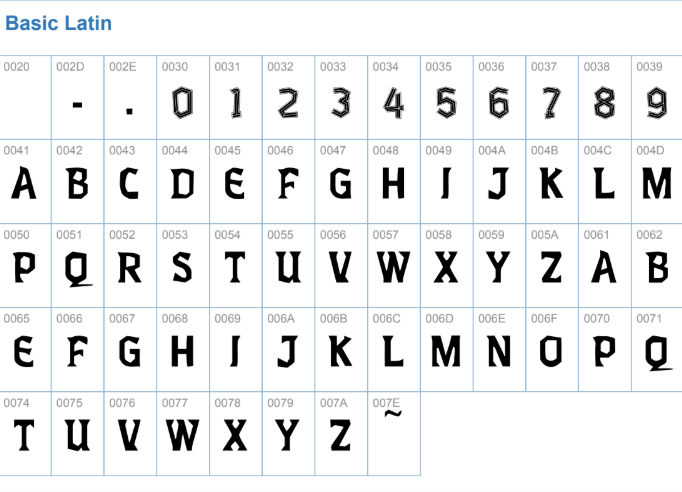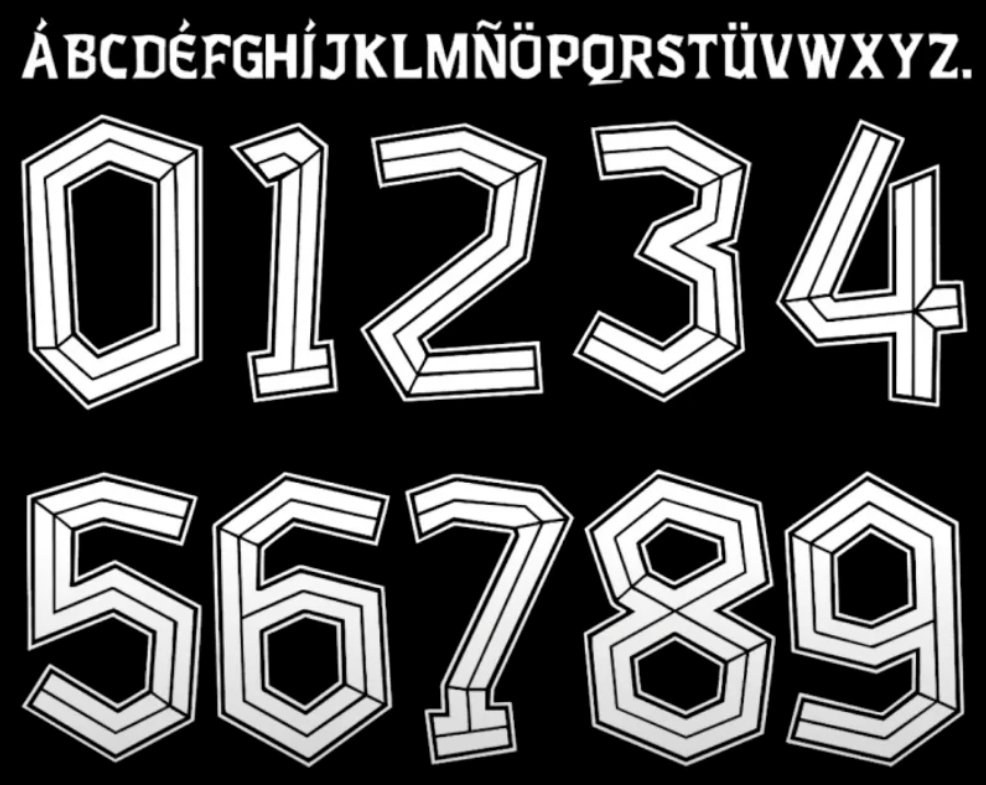
Para os apaixonados pelo Vozão e profissionais de personalização esportiva, trazemos hoje um arquivo essencial: a tipografia oficial utilizada nos uniformes do Ceará Sporting Club para a temporada 2024.
Sabemos que o Ceará se destaca no cenário nacional não apenas pela sua torcida apaixonada, mas também por ser um dos pioneiros a ter sua própria marca de material esportivo, a Vozão. Isso garante uma identidade visual única, fugindo dos padrões genéricos de grandes fornecedoras globais como Nike ou Adidas. Com esta fonte, você poderá reproduzir fielmente os nomes e números das camisas de jogo (Home e Away) utilizadas no Campeonato Brasileiro e demais competições do ano.
Estilo Visual e Identidade
A tipografia de 2024 do Ceará segue uma linha moderna e geométrica, transmitindo robustez e agressividade, características que combinam perfeitamente com o peso da camisa alvinegra.
Diferente de fontes mais arredondadas ou clássicas, os números apresentam cortes angulares estratégicos e uma espessura (bold) que garante excelente leitura tanto no estádio quanto na transmissão televisiva. É o design ideal para quem busca criar mockups realistas, personalizar camisas de torcida ou trabalhar com sublimação de alta fidelidade.
- Conteúdo: Alfabeto completo (caixa alta) e numeração oficial 2024.